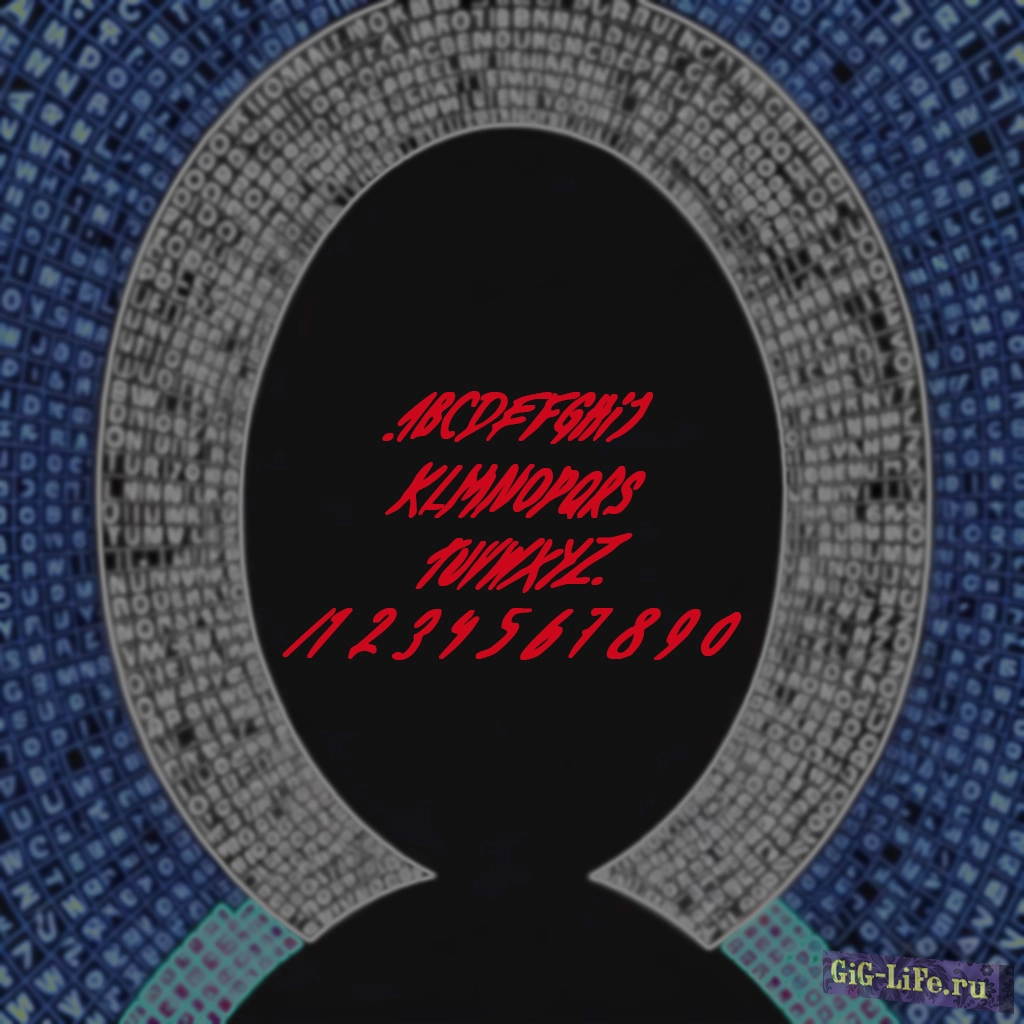
Шрифт Flubber — это настоящий шедевр в мире типографики, созданный для тех, кто ценит оригинальность и креативность. Его плавные, растекающиеся формы создают уникальный визуальный эффект, который сразу же привлекает внимание. Каждая буква в этом шрифте словно живая, она дышит и движется, придавая любому дизайну неповторимую динамику.
Этот шрифт идеально подходит для оформления обложек книг, постеров, рекламных материалов и даже личных проектов в Photoshop. Его плавные линии и мягкие формы создают атмосферу волшебства и чуда, что делает его идеальным выбором для тех, кто хочет выделиться и произвести впечатление.
Шрифт Flubber — это не просто набор букв, это инструмент для создания визуальных историй, где каждая буква становится частью магического и завораживающего мира. Он позволяет выразить самые смелые идеи и фантазии, делая каждый проект уникальным и запоминающимся.